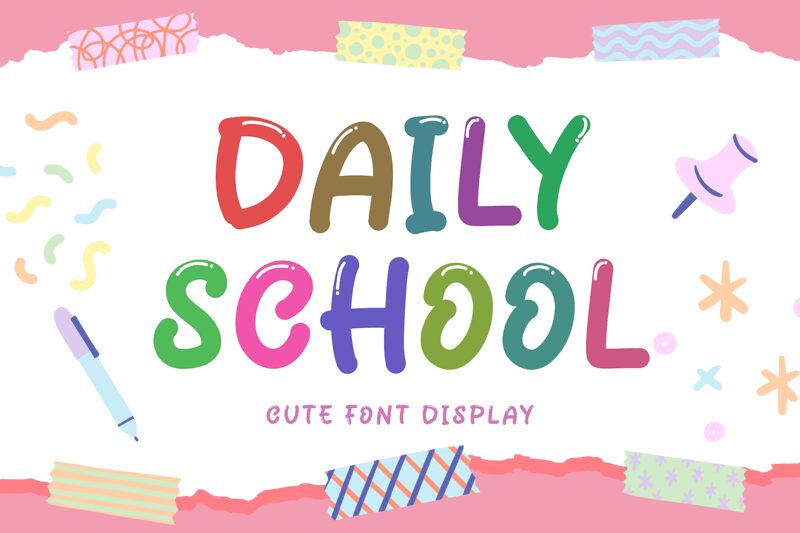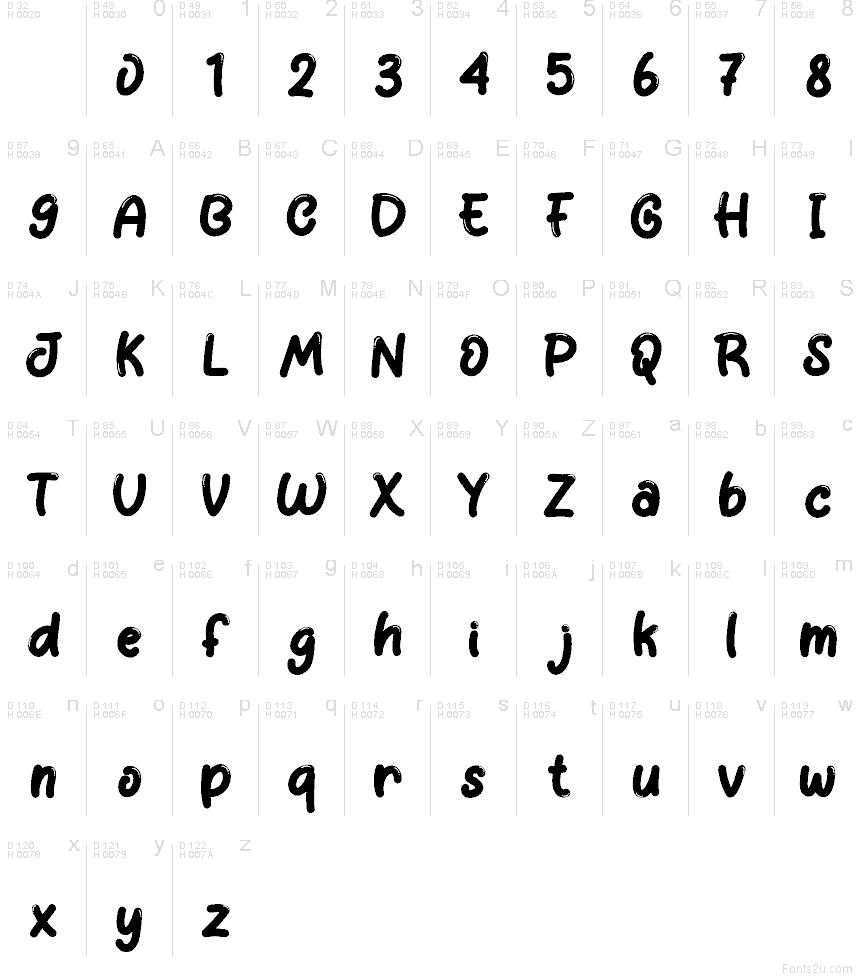
Daily School Demo
Daily School é uma fonte gratuita de estilo cartoon, com letras arredondadas feitas à mão que lembram notas de escola. As formas são levemente irregulares e amigáveis, com curvas suaves que mantêm o visual descontraído e informal em vez de rígido.
Daily School funciona muito bem em cartazes de sala de aula, folhas de atividades infantis, flyers de eventos escolares, banners de reforço escolar e títulos de estilo gibi, pois traz um toque manuscrito e acessível para textos curtos. Esta fonte gratuita também é perfeita para etiquetas e gráficos alegres para redes sociais, quando você busca uma tipografia com um ar leve e pessoal, sem perder o seu claro caráter de desenho animado.